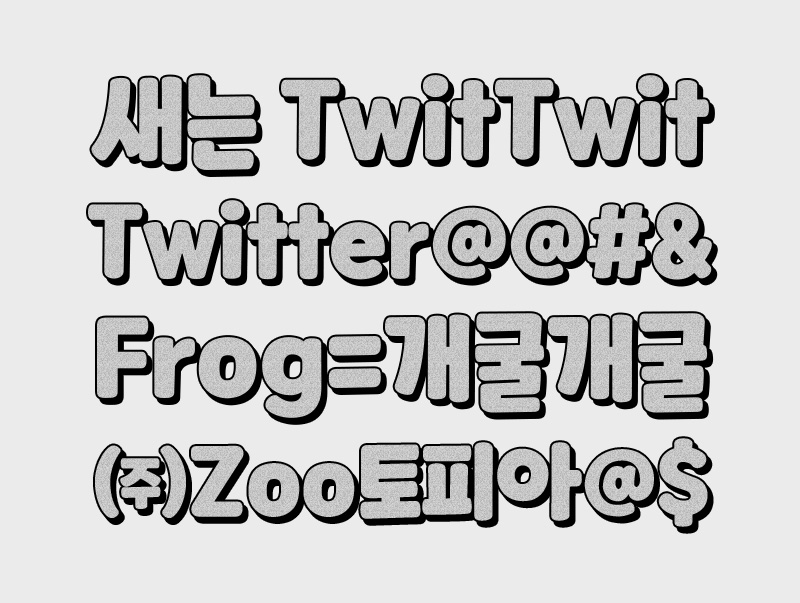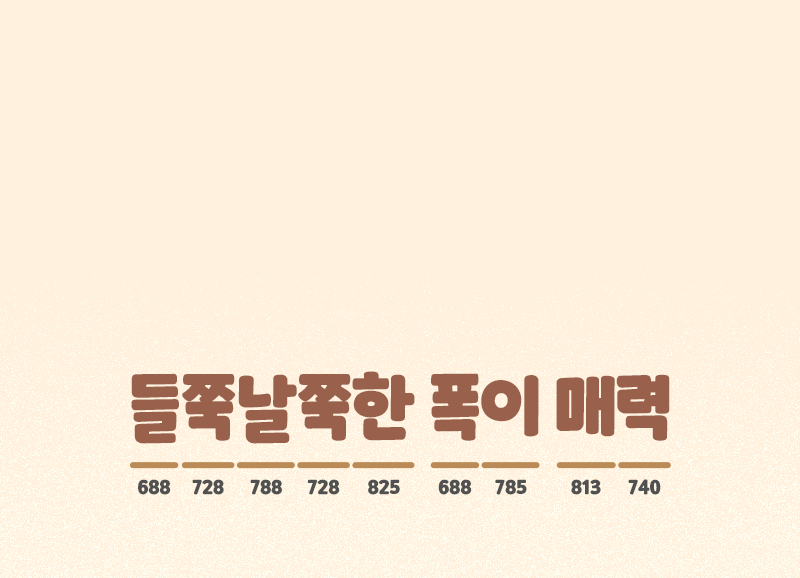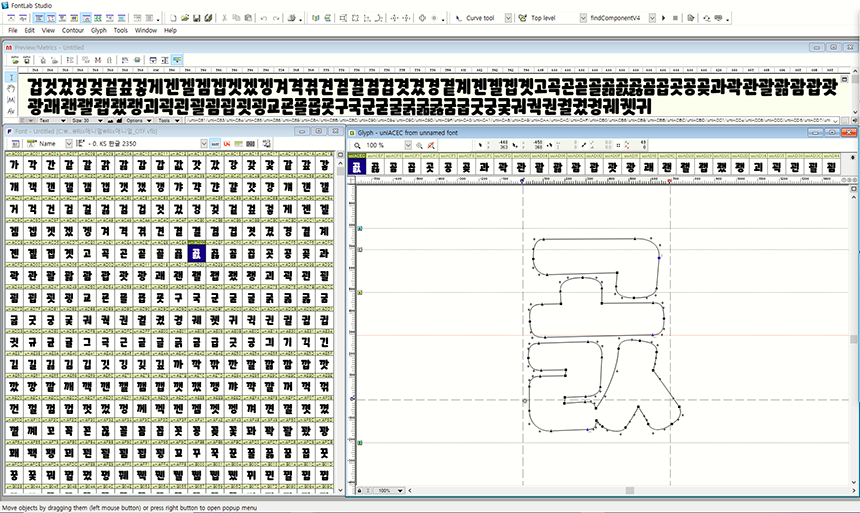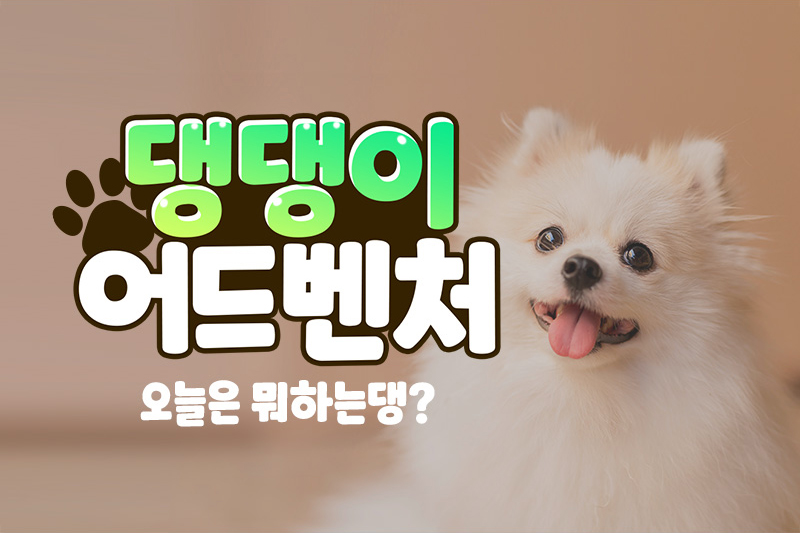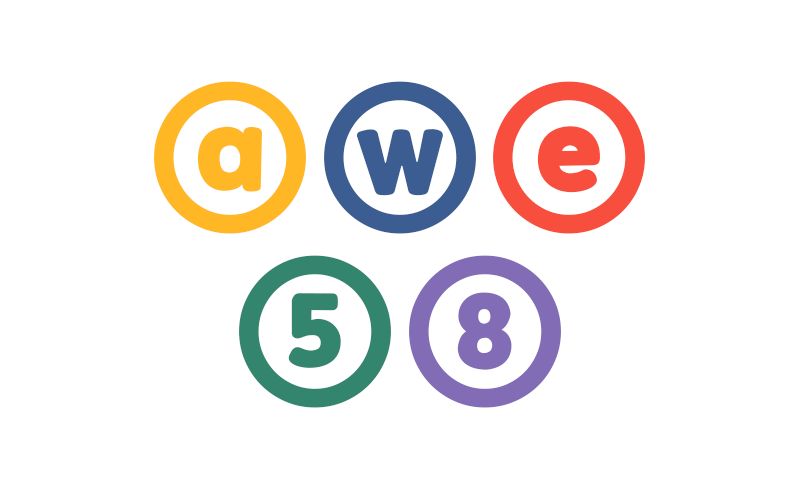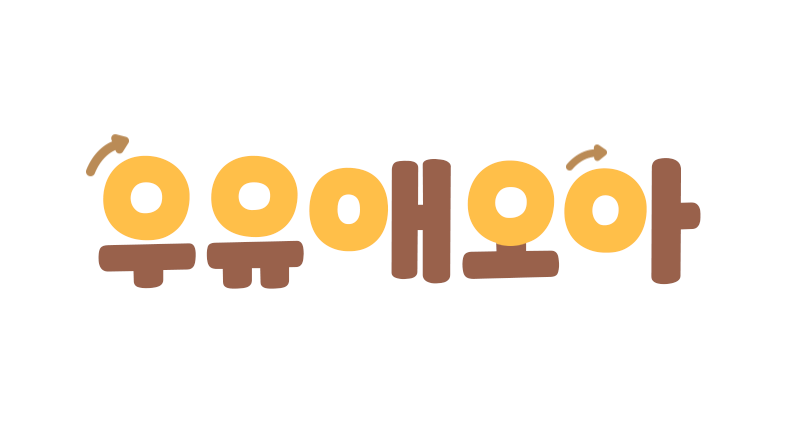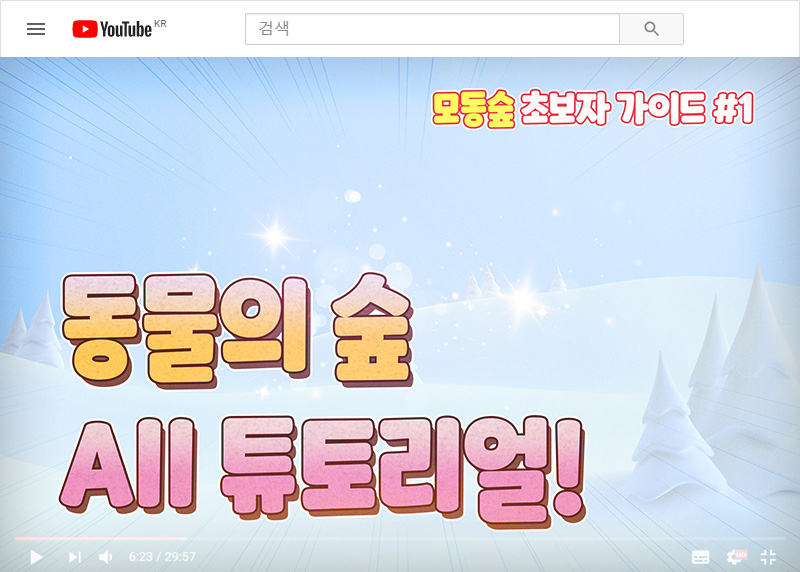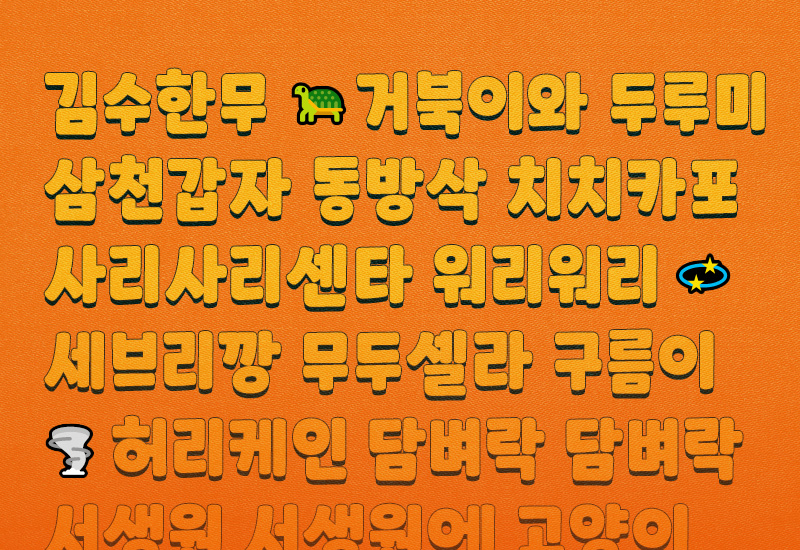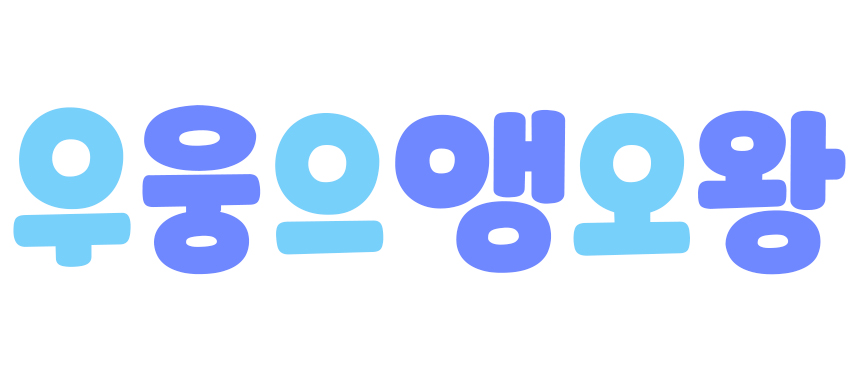
동글동글 귀엽고 친근한, Rix애니멀
댕냥이들도 신이 나는 볕 좋은 5월, 천방지축 귀여운 동물 친구들을 닮은 서체「Rix애니멀」폰트를 소개합니다! 두툼하고 오동통한 두께와 둥글게 굴러가는 획이 너무나 친근하고 귀여운 폰트입니다. Rix애니멀을 제작해주신 이강우 디자이너의 이야기 들어보지 않을 수 없겠죠~ 함께 만나볼까요?
안녕하세요, 이강우 디자이너님. Rix심야식당 이후로 오랜만에 인사드립니다~ 새로운 폰트와 함께 돌아오셨네요!
네, 안녕하세요! 이강우 디자이너입니다. 이번에 신서체 Rix애니멀 폰트로 인사드리게 됐습니다.
이번에 제작하신 폰트에 대해 간단한 소개 부탁드려요!
우선 동글동글 귀여운 폰트를 만들어보고 싶었는데 그러는 와중에 가변폭으로 'ㅇ'을 정원에 가깝게 표현할 수 있지 않을까 하는 생각이 들었어요. 그래서 *종성이 있더라도 최대한 정원에 가까운 *초성 'ㅇ'으로 표현을 하였고, 'ㅡ', 'ㅜ'와 함께 있는 'ㅇ'도 글줄에 크게 문제가 되지 않는 선에서 동그랗게 제작했습니다.
*종성: 음절의 구성에서 마지막 소리인 자음, 즉 받침을 뜻합니다.
*초성: 음절의 구성에서 처음 소리인 자음. '님'에서 'ㄴ'이 초성.
폰트명 '애니멀'이 정말 귀여워요. 폰트와 잘 어울리기도 하고요! 어떻게 짓게 된 이름인지 궁금합니다.
평소에 동물 유튜브를 많이 보는 편인데 주로 반려견, 반려묘 위주의 채널이 많잖아요. 그런 곳에서 쓰인 자막용 폰트들을 보면서 '이런 데 이 폰트가 많이 쓰이게 되지 않을까' 또는 '많이 쓰였으면 좋겠다' 싶은 아이디어 반, 기대 반으로 지어진 이름입니다. 동물들이 귀엽고 또 전체적인 채널 콘셉트들이 귀여움에 포커스가 맞춰져 있다 보니 아무래도 어울리지 않나 하는 생각이 들었습니다. 여러 네이밍 후보가 있기도 했지만 초기 기획 단계에서 구상한 이 이름이 결과적으로 폰트와 가장 잘 어울린다는 평이 많아 그대로 가게 되었어요.
획이 꽤 도톰한 폰트인데요, 모양을 잡을 때 가장 신경 쓴 부분이 무엇인지!
획이 굵다 보니 겹쳐지는 부분이 많았고, 이 부분을 어떻게 처리할까를 가장 고민했던 것 같습니다. 또 꼴(글자) 별로 모양이 조금씩 달라지다 보니 획을 조절할 수 있는 여지가 각각 달라서 특히 신경 써서 작업했던 것 같아요.
폰트 디자인 프로세스
굉장히 세밀한 작업이 필요했겠어요. 제작자로서 "이 폰트의 가장 큰 매력 포인트는 OO이다."라고 표현해 주신다면?
이 폰트의 가장 큰 매력 포인트는 동그란 정원 초성 'ㅇ'이라고 말하고 싶고, 또 들쭉날쭉한 글줄로 귀여움이 배가 된 폰트라고 할 수 있을 것 같습니다.
혹시 폰트디자이너가 아니었다면 어떤 일을 하셨을 것 같은지?
아직 잘 상상은 가지는 않네요.. 딱히 생각해 본 적은 없는데 아마 원래 전공인 영상 쪽 일을 하고 있지 않았을까 하는 생각입니다.
원래 전공이 영상 디자인이셨는데 폰트 디자인 쪽으로 취업하게 된 계기가 있을까요?
영상을 툴과 테크닉 위주로 배우다 보니 정작 어떻게 디자인하는가에 대해서는 혼자서 공부를 할 수밖에 없었는데 그러다가 시각디자인에 관심을 갖게 되었습니다. 시각디자인 중에서도 폰트 디자인이 디자인의 A-Z라는 생각이 들었고 디자인의 근본이 되는 폰트를 만드는 쪽으로 취업을 하게 된 것 같습니다.
현업에서 영상 스킬도 활용 중이신 능력자신 걸로 알고 있습니다👍 마지막으로 강우 디자이너가 생각하는 좋은 폰트란?
사람들이 보기에 쓰고 싶다는 생각이 들고, 많이 써주시는 폰트가 좋은 폰트이지 않나 하는 생각입니다. 아직 어떤 게 완성도가 높은 것인가 완성도 높은 게 좋은 것인가 판단하기에는 부족하다는 생각도 들어서요.(웃음)
생동감 넘치는 손글씨 서체
두꺼운 마카로 쓴 듯 두툼하고 단단한 획에 모든 자소의 꺾임이 둥글게 굴려진 마무리감이 부드러운 형태를 가지고 있습니다. 생동감 넘치는 동물 친구들처럼 리드미컬한 글줄과 들쭉날쭉한 가변폭이 특징입니다.
어! 귀엽다. 동그란 이응꼴
Rix애니멀의 가장 큰 특징이기도 한 동글동글한 초성 'ㅇ'은 정원형에 가장 가깝게 설계되었습니다. 전체적으로 귀엽고 사랑스러운 느낌이 나도록 디자인되었습니다.
디자이너가 인터뷰에서 언급했듯이 'ㅇ'이 받침에 들어갈 때에도 가독성을 해치지 않는 범위 내에서 최대한 둥글게 표혔했는데요. 약간은 가로로 길어지긴 하지만 모서리가 둥근 사각형이 아닌 타원의 형태를 유지하고 있는 모습입니다. 자세히 보면 어떤 자소와 만나느냐에 따라 받침 'ㅇ'의 모양도 계속 달라져 손글씨의 묘미를 느낄 수 있어요.
통일감을 준 컨셉
동글동글 귀여운 한글 컨셉의 특징을 영문, 숫자, 특수문자에도 동일하게 적용하여 폰트에 통일감을 주었습니다. 어떠한 조합으로 만나더라도 이질감이 느껴지지 않도록 디자인하여 조화롭게 연출할 수 있습니다.
| 이렇게 활용해 보세요!
귀여운 동물 친구들에게 모티브를 얻은 폰트인 만큼 통통 튀는 유튜브 채널 썸네일 또는 배너 디자인으로 활용하기 좋아요. 눈에 쉽게 들어오는 큼직한 크기로 테두리를 넣어 더욱 돋보이게 사용해 보세요.
'귀여움' 하면 또 빼놓을 수 없는 어린이들이 있죠. 친근하고 부드러운 서체의 특징이 아이들과 관련된 각종 시각물이나 인쇄물, 웹 페이지 등 다양한 부분에 활용하기 좋습니다. 코로나 19 방역지침과 같은 주제도 무겁지 않게 풀어낼 수 있고😷 곧 다가오는 어린이날 행사 등 즐거운 소식도 담기에 좋은 폰트입니다🎈
이렇게 5월의 신서체 Rix애니멀 서체를 만나봤는데요. 부쩍 햇살이 오래 머물고 따뜻해진 날씨만큼, 기분 좋은 문구와 내용에 쓰였으면 좋겠다는 생각이 드네요. 귀염뽀짝 애니멀 폰트로 쓸 기쁘고 신나는 소식들이 더 가득가득했으면!